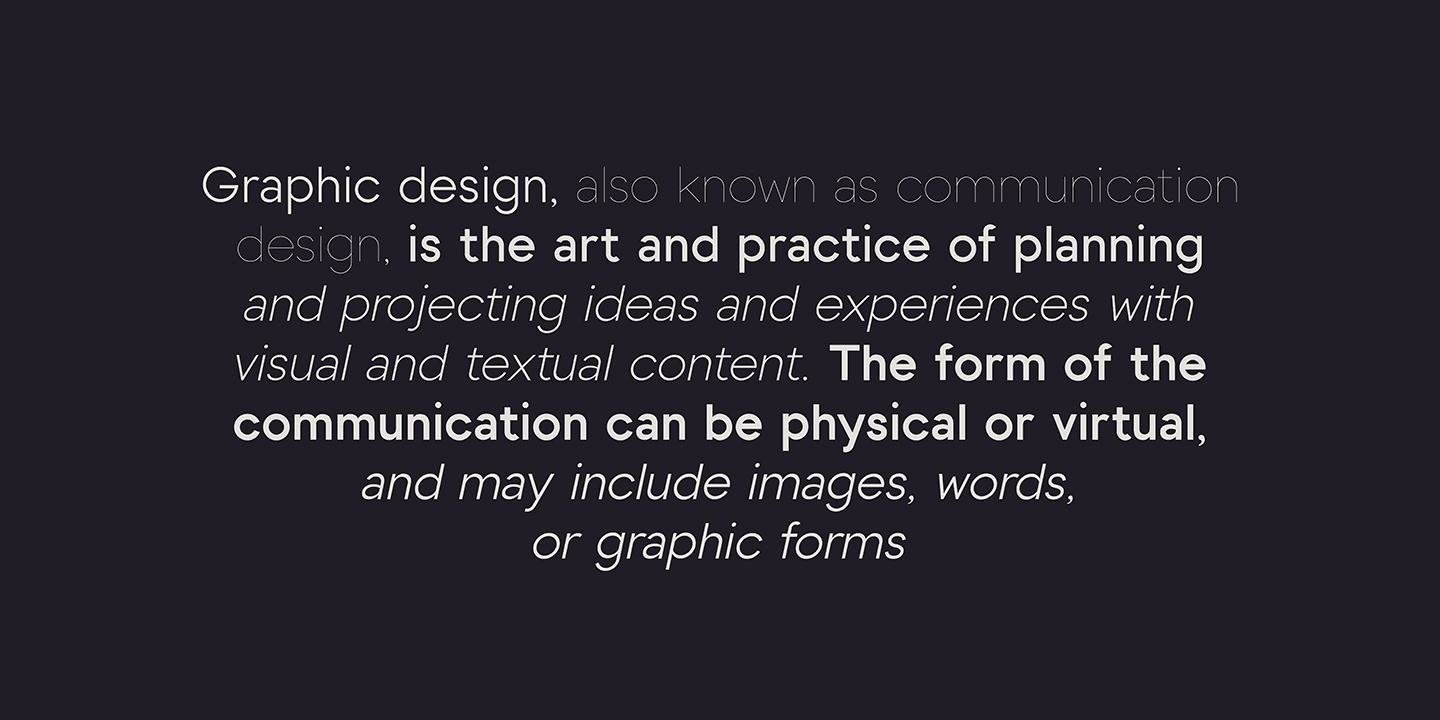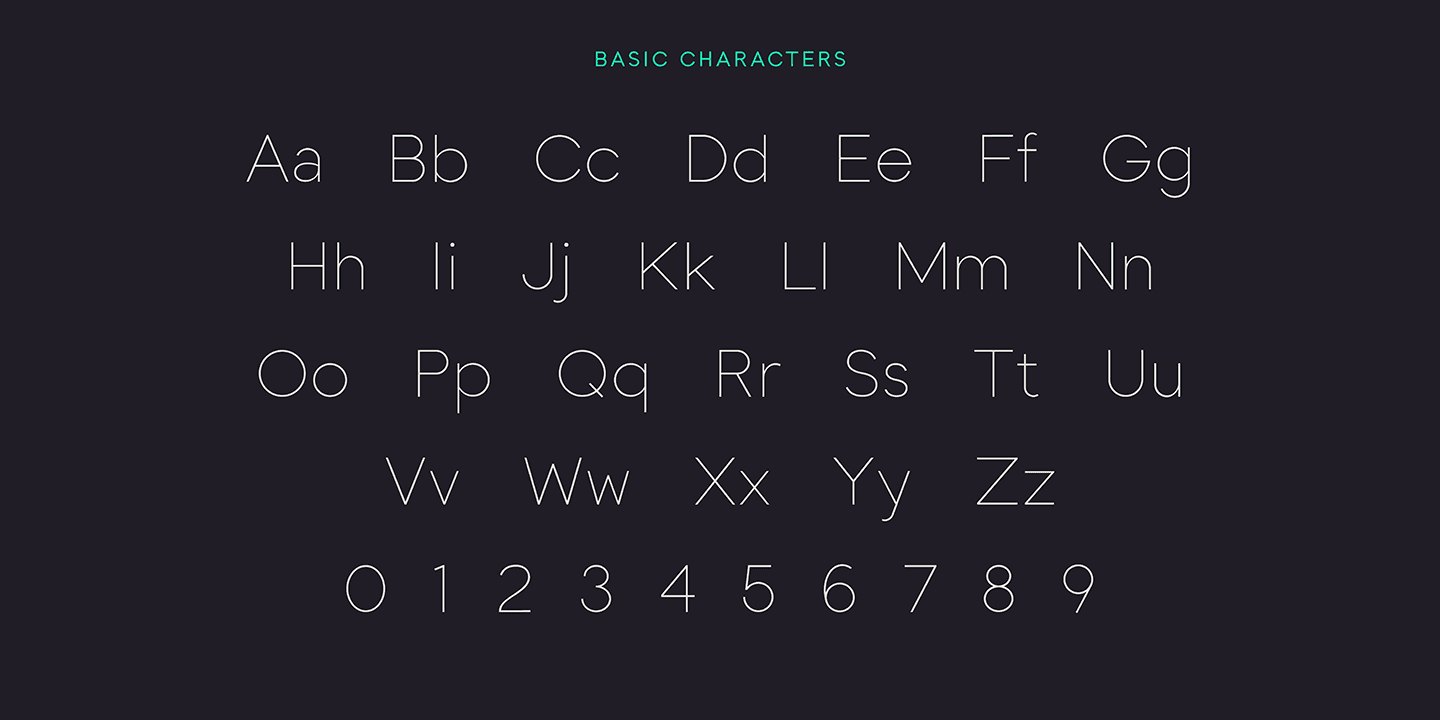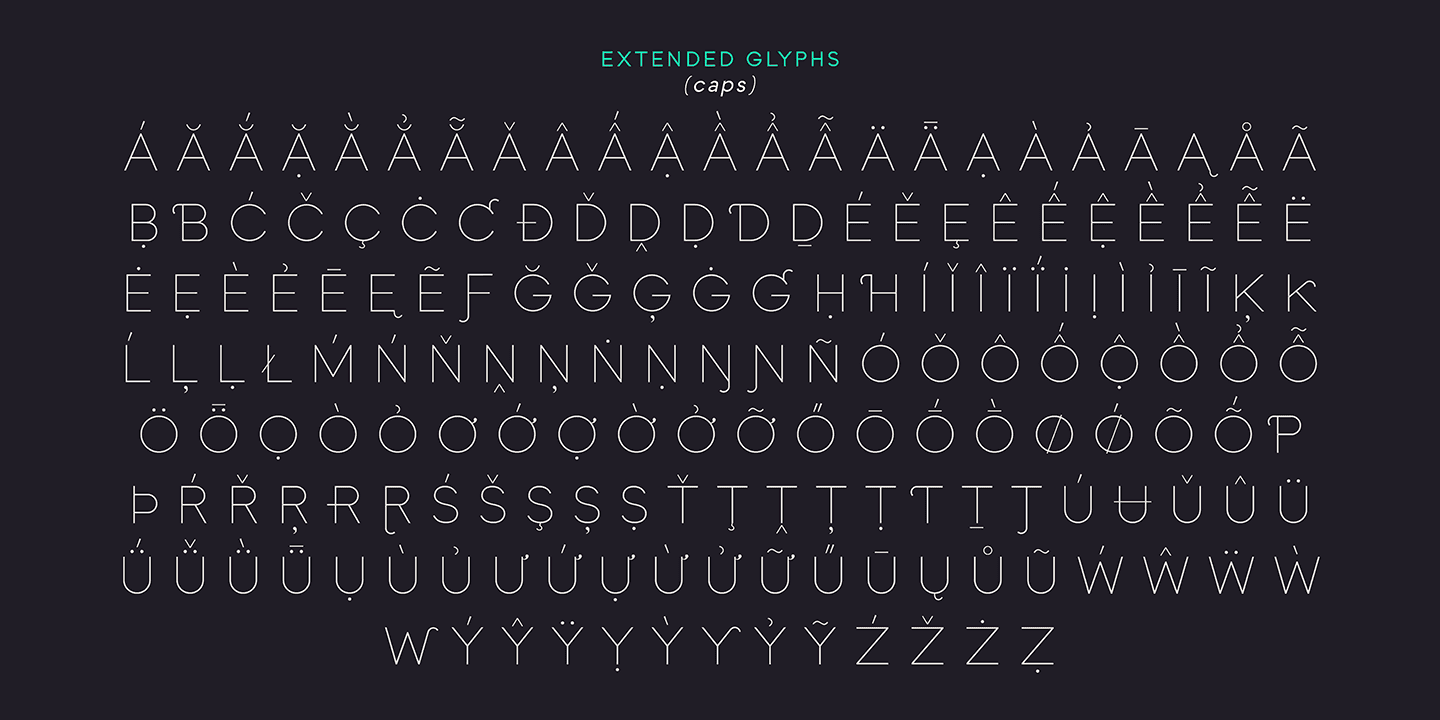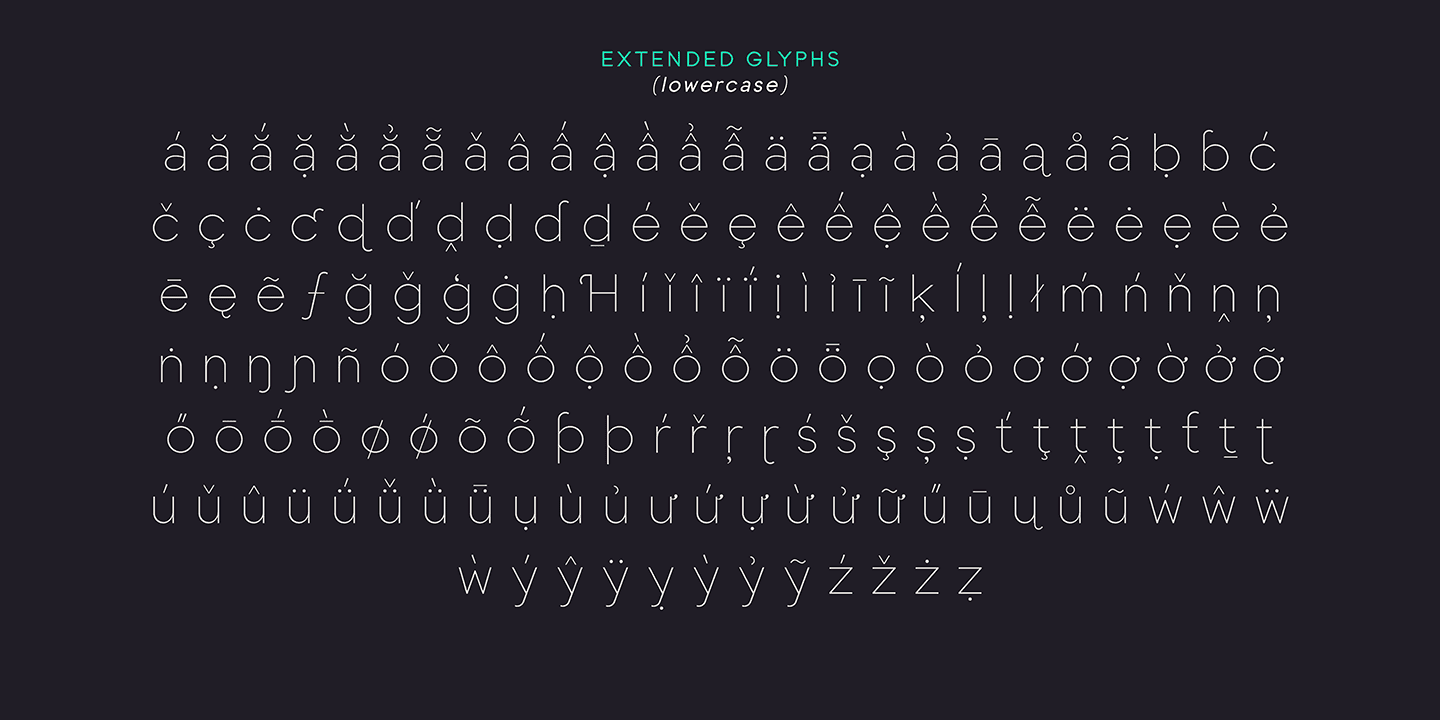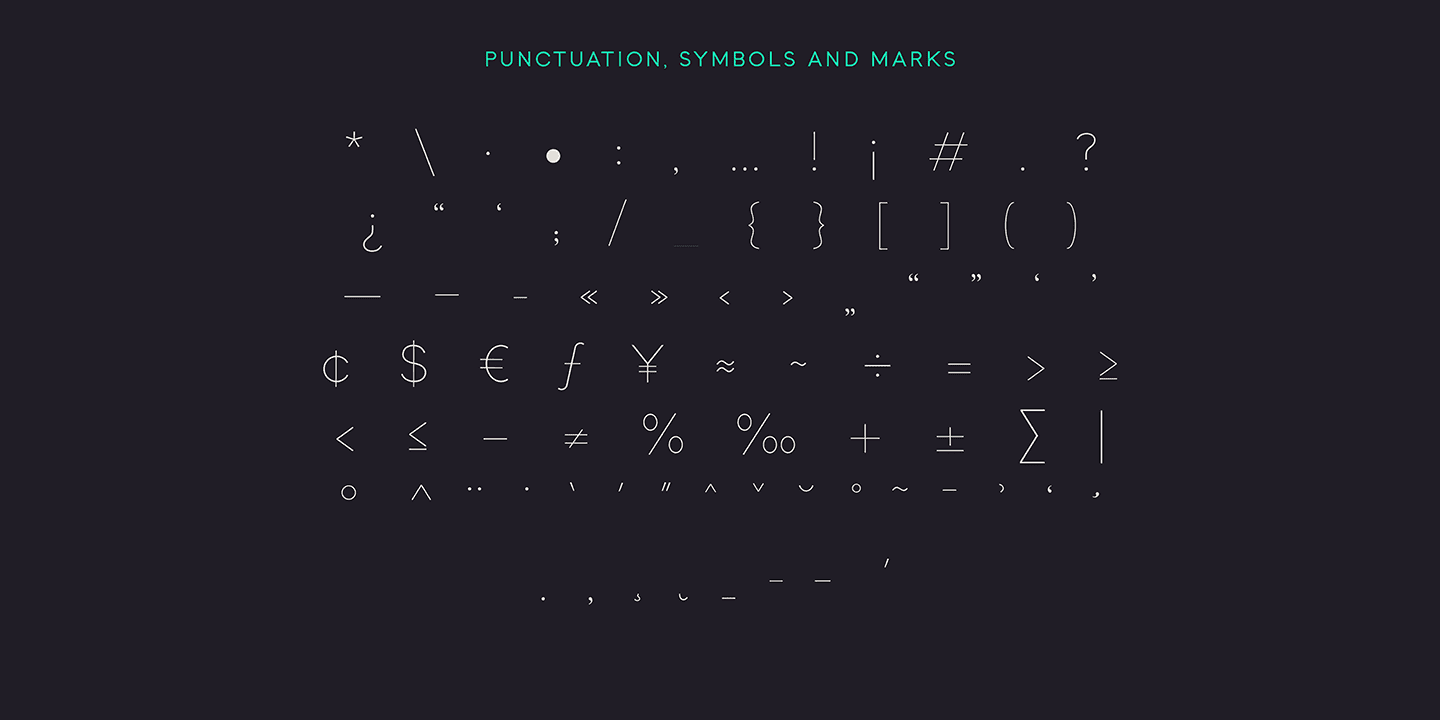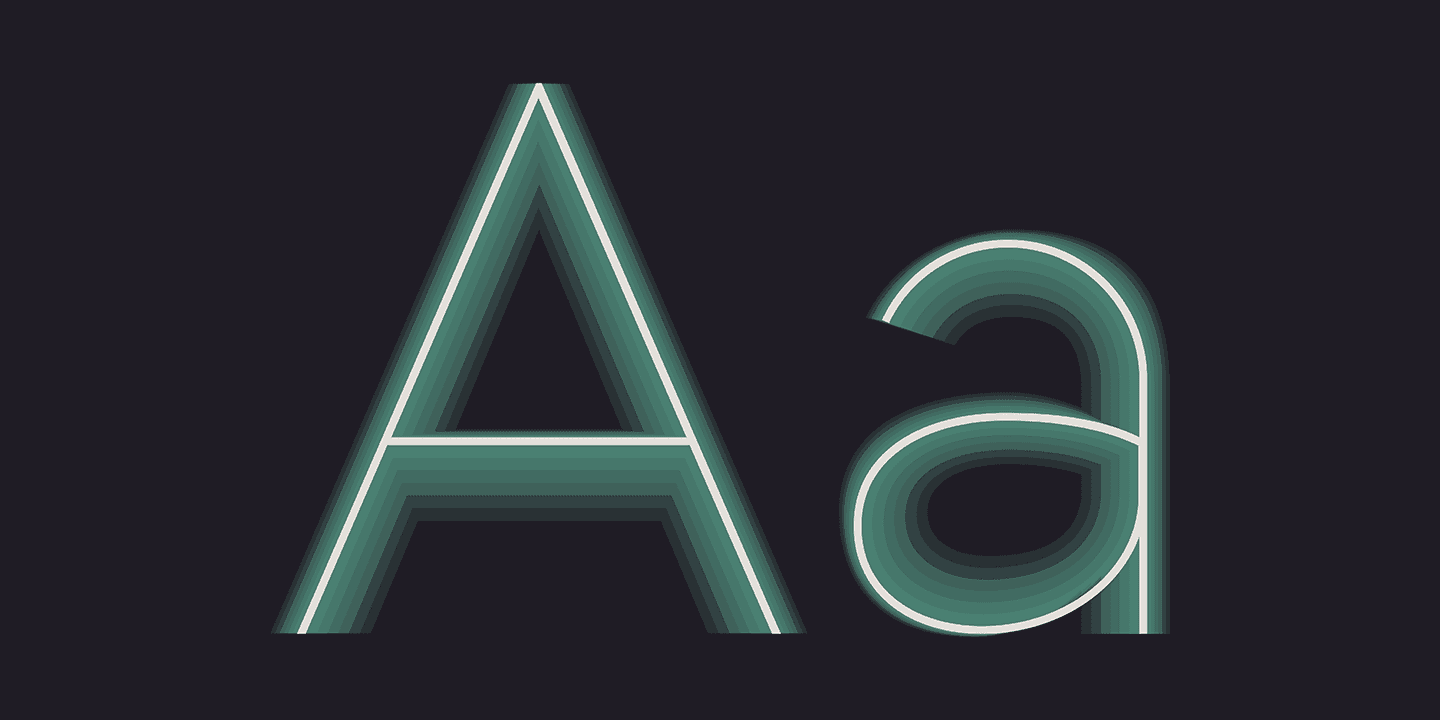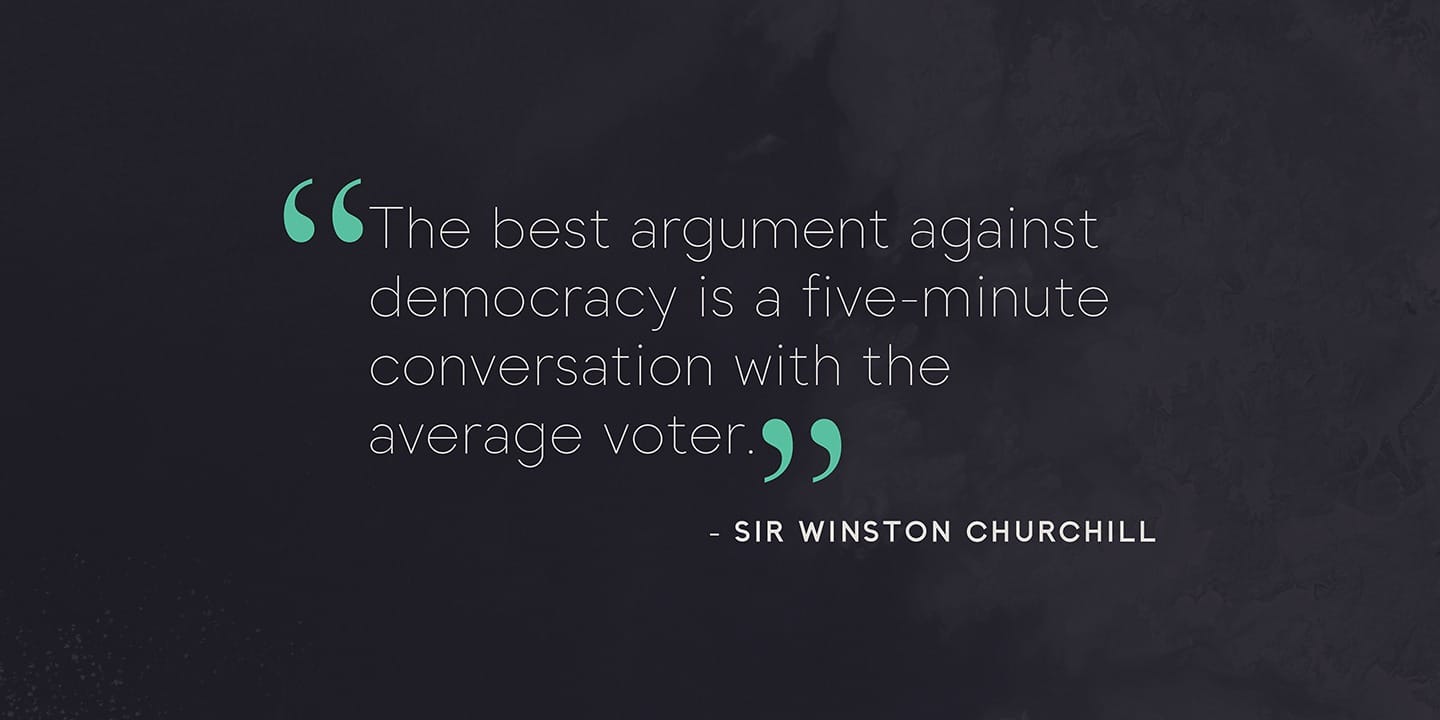
Toma Sans Font Family là một bộ font kiểu sans serif. Bị ảnh hưởng bởi các mặt sans serif kiểu hình học phổ biến trong những năm 1920 và 30, các phông chữ dựa trên các dạng hình học đã được hiệu chỉnh để dễ đọc hơn.
Bộ font Toma Sans Font Family này gõ được Tiếng Việt nhé các bạn.